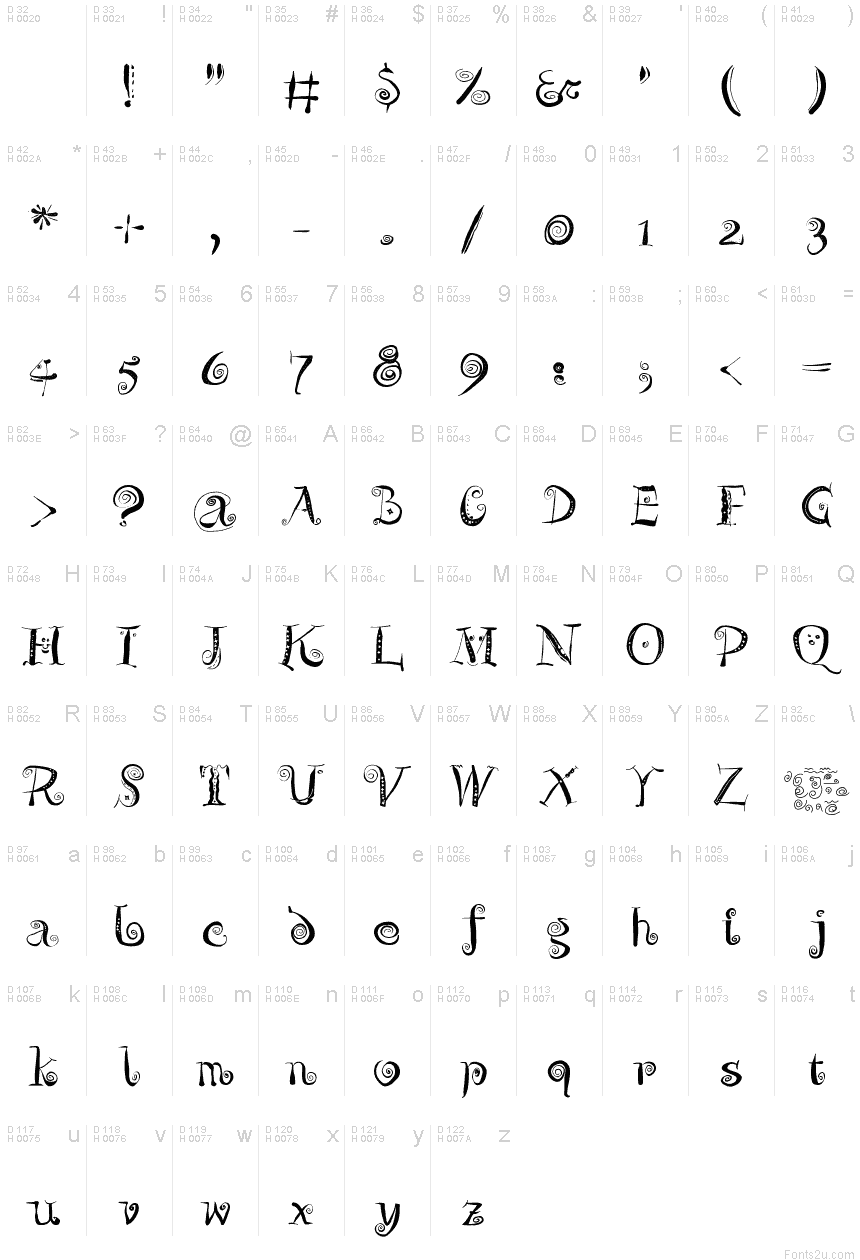
Zeit Geisterbahn von Manfred Klein ist eine kostenlose, verspielte Display-Schrift mit einem subtilen Art-Nouveau-Touch. Die Buchstaben kombinieren drahtige, handgezeichnete Konturen mit engen Spiralen, was der Schrift eine leicht unheimliche, theatralische Note verleiht, statt sie nur dekorativ wirken zu lassen.
Sie eignet sich hervorragend für Plakate, Buchcover, Musik-Flyer, Titelkarten, Café-Branding und Halloween-Grafiken, bei denen eine kostenlose Schrift einen Hauch von altem Jahrmarkt-Drama braucht. Da sich die Kringel wiederholen, während die Hauptstriche schlank und hoch bleiben, ist sie ideal für kurze Überschriften, Initialen und Monogramme, die Bewegung brauchen, ohne zu einem dichten Block zu werden.